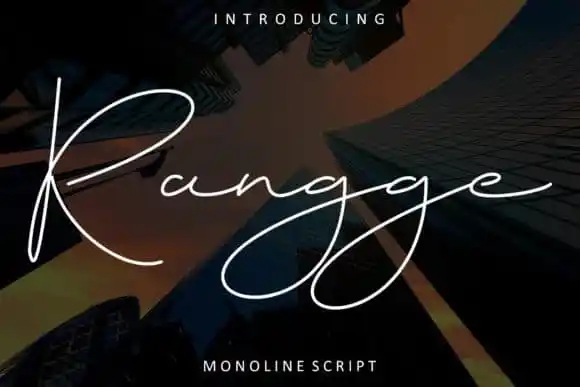
Rangge Handwritten Font – Download Grátis
A Rangge Handwritten Font é uma magnífica tipografia serifada em monolinhas que abraça os sentidos com seu charme elegante e força sólida, presenteando cada glyph de forma sofisticada mas robusta. Este tipo de fonte foi criado pelo designer do 99designs, insanurbahagia, e é perfeitamente adequada para a criação de logos impactantes, marcas distintivas e frases inspiradoras. Com suas letras únicas e belas, essa fonte traz um toque especial às criações gráficas, iluminando o design. Seja ela usada em materiais visuais como identidades corporativas ou em uma frase poética para criar um impacto visual único e atraente, Rangge Handwritten é certamente uma escolha ótima para designers apaixonados por adicionar um toque especial ao seu trabalho.